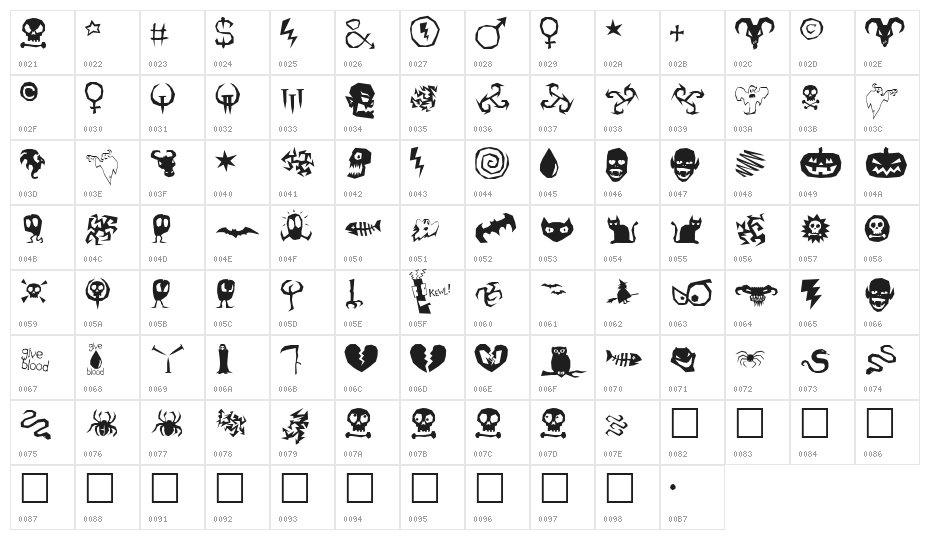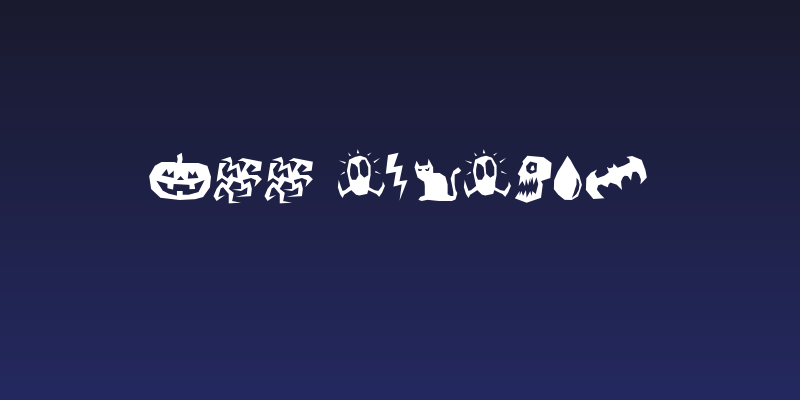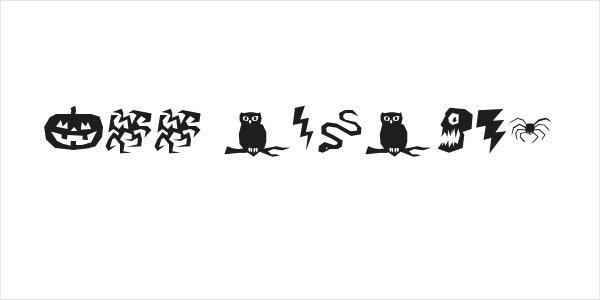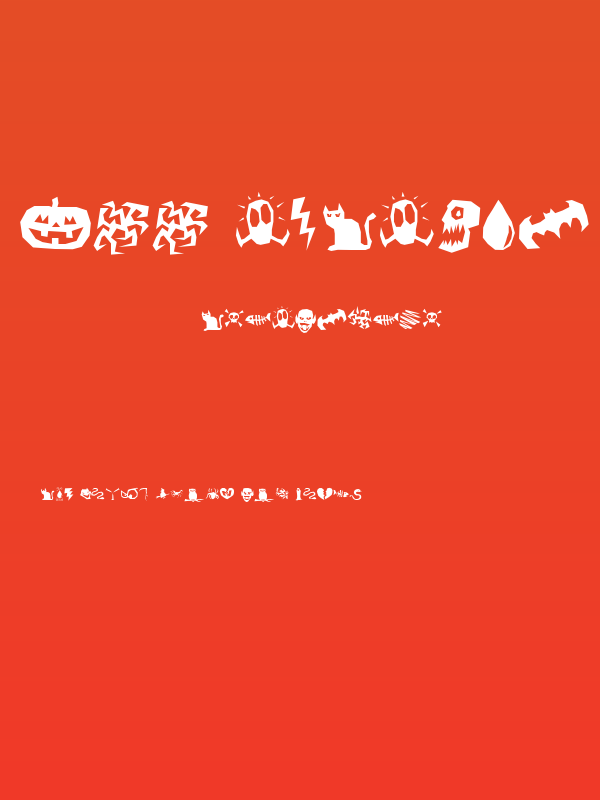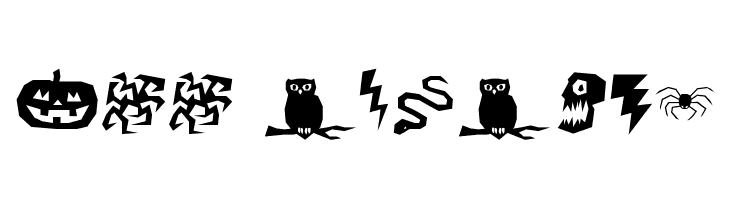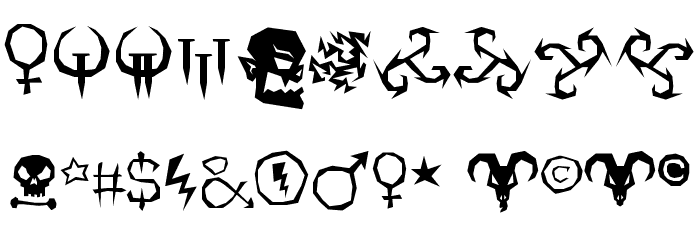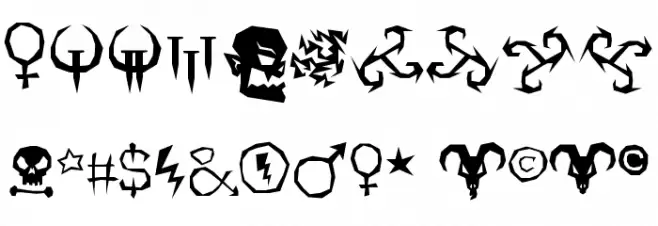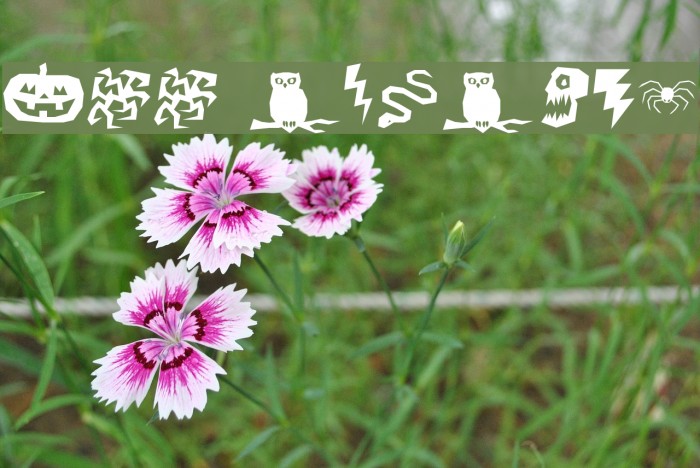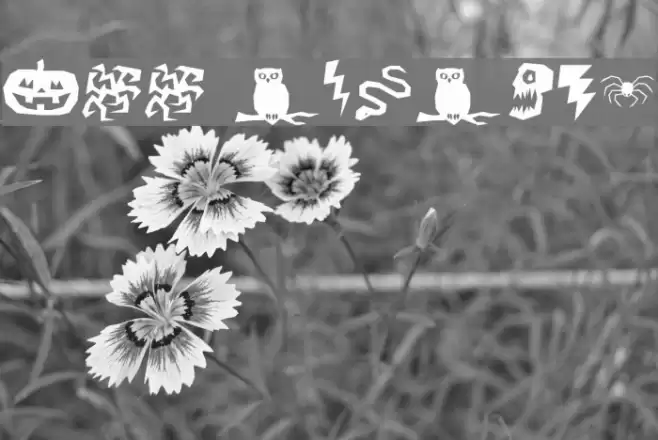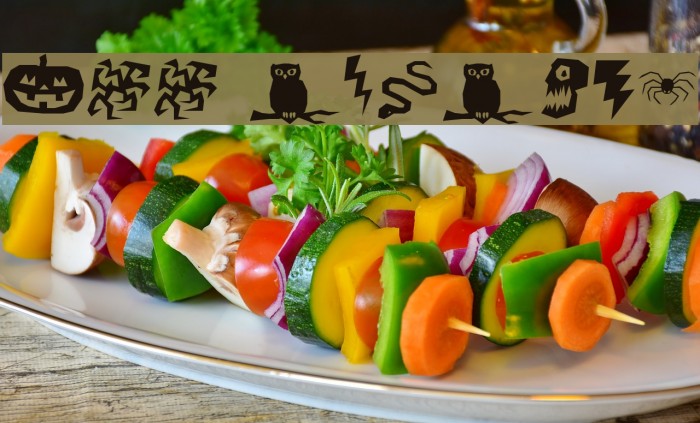
ILL oCtoBer Font
| Gesamtstil | Decorative, Playful, Spooky |
| Anwendungsfall | Headlines, Posters, Themed Graphics |
| Vorgeschlagene Projekte | Halloween party invitations, themed posters, event flyers, children’s crafts, seasonal branding, decorative headlines. |